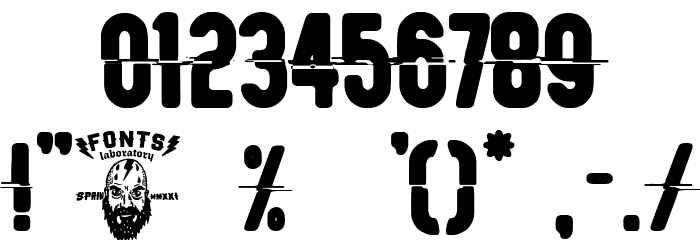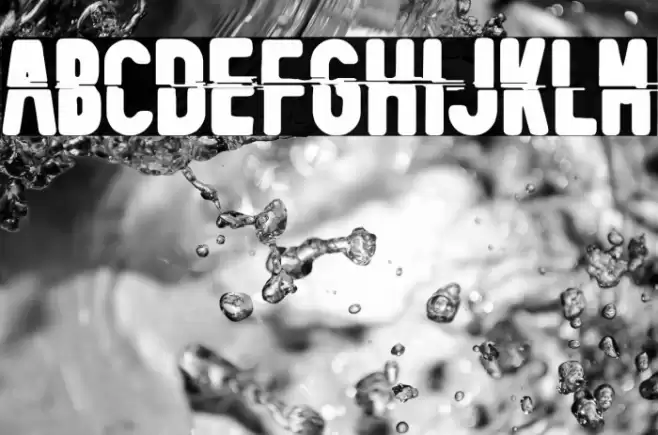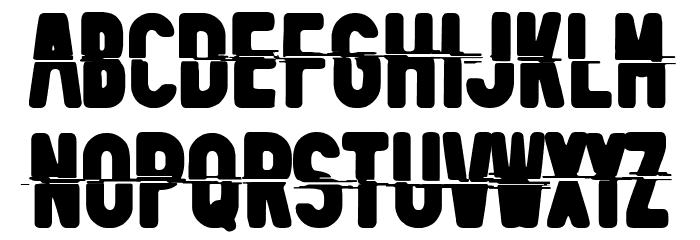
Mecanico Industrial Font
✎ Distorted Eroded
| Projets proposés | Ideal for urban-themed posters, industrial branding, edgy apparel designs, and modern logos. |